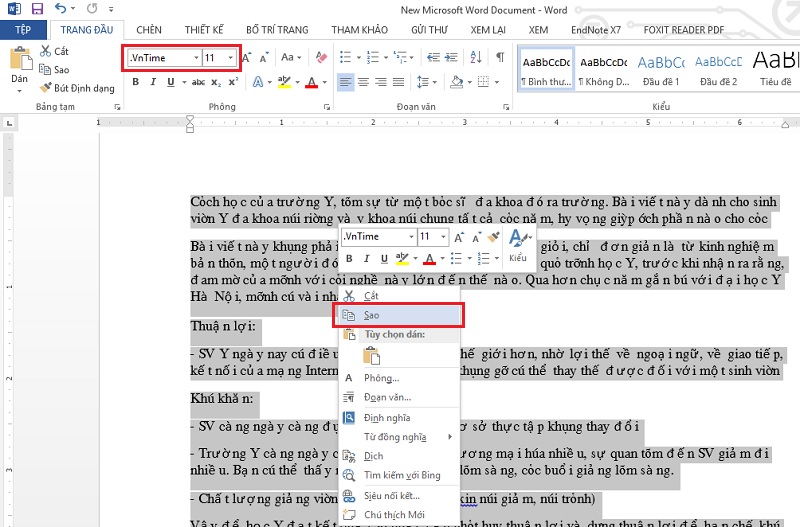
Bộ font chữ TCVN3 đầy đủ
Bộ font ABC hay còn gọi là font Tiêu chuẩn Việt nam 3 (TCVN3) gồm những font chữ thông dụng trước kia như .VNTime, .VNArial... và có thể sử dụng với nhiều bộ gõ tiếng Việt như Unikey, VietKey... Hoatieu.vn xin gửi tới bạn đọc bài viết bộ font chữ TCVN3 - Font chữ VnTime để bạn đọc cùng tham khảo và có thể hiểu rõ hơn về bộ font chữ TCVN3.
Font TCVN3 là bộ font chữ do Viet Nam tạo ra thường được sử dụng trong SGK của các em học sinh do những ưu điểm vượt trội như: nhiều font tiếng Việt đẹp miễn phí, nhiều font ABC chữ hoa, chữ thường, các font chữ đa dạng, nhiều lựa chọn.....
Bộ font chữ TCVN3 - Font chữ VnTime
1. Font TCVN3 là gì?
TCVN3 là bảng mã tiêu chuẩn (cũ) của Việt Nam bao gồm tất cả những font chữ có .Vn đứng đầu. Do đó khi đọc hoặc làm việc với các font chữ có định dạng .Vn này đòi hỏi bạn phải chọn bảng mã phù hợp là TCVN3 ( hay ABC).
Những tài liệu học tập, văn bản khi tải xuống từ Internet có khá nhiều loại sử dụng font chữ này, nhất là những tài liệu được soạn thảo từ thời gian mấy năm trước. Nếu không có bộ font TCVN3 trong máy thì bạn sẽ không thể hiểu được nội dung văn bản đó nói gì vì lỗi font quá nặng.
2. Font TCVN3 dùng để làm gì?
Bộ Font TCVN3 phong phú là font chữ tiếng Việt tiêu chuẩn nước ta rộng lớn nhất hiện nay với với font chữ căn bản như: .VNTime, .VNArial, vv. Bộ Font TCVN3 đầy đủ sẽ giúp bạn có thể nhập tiếng Việt khi biên soạn văn bản, thiết kế, trò chuyện trên các sử dụng chat và bộ font TCVN3 tương thích với bộ gõ tiếng Việt: Unikey, Vietkey, vv.
Bộ Font TCVN3 đầy đủ không chỉ có các font chữ tiếng Việt cơ bản mà còn có không hề ít mẫu chữ đẹp mang tính nghệ thuật cao. Các font chữ này cũng có khả năng sử dụng để làm Website, thiết kế hay tạo slide cho thật đẹp đẽ khi sử dụng: font chữ thư pháp, font nét phấn, vv. Mỗi mẫu chữ đều mang những đặc trưng riêng biệt hỗ trợ bạn thoải mái thông minh theo cách riêng của chúng ta.
4. Đặc điểm nổi bật của Font TCVN3
- Cung cấp hệ thống phông chữ đa dạng.
- Khả năng tương thích với hệ điều hành cao, với Vietkey, Unikey… lớn.
- Thao tác chọn Font TCVN3 thông qua Unikey dễ dàng
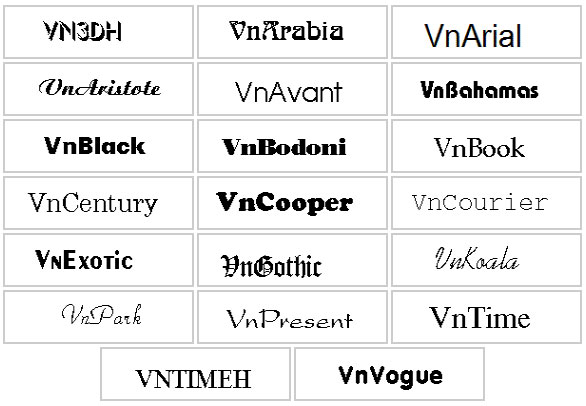
Sử dụng TCVN3 sẽ mang lại cho bạn những cảm xúc rất đặc biệt, vì cách soạn thảo sẽ không giống như khi bạn gõ chữ với Unicode. Gõ "lò dùng sóng" sẽ thành "lũ dựng súng", "lè nhè" → "lố nhố", "lâng bâng" → "lõng bõng", "tê mê" → "tờ mờ". Vì là tiêu chuẩn cũ, nên ta thường bắt gặp chuẩn này trong những tài liệu tương đối "cổ". Dù hiện tại, ít người sử dụng chuẩn này, nhưng vẫn sẽ cần đến nó để đọc được các tài liệu hoặc sử dụng trong những yêu cầu đặc biệt.